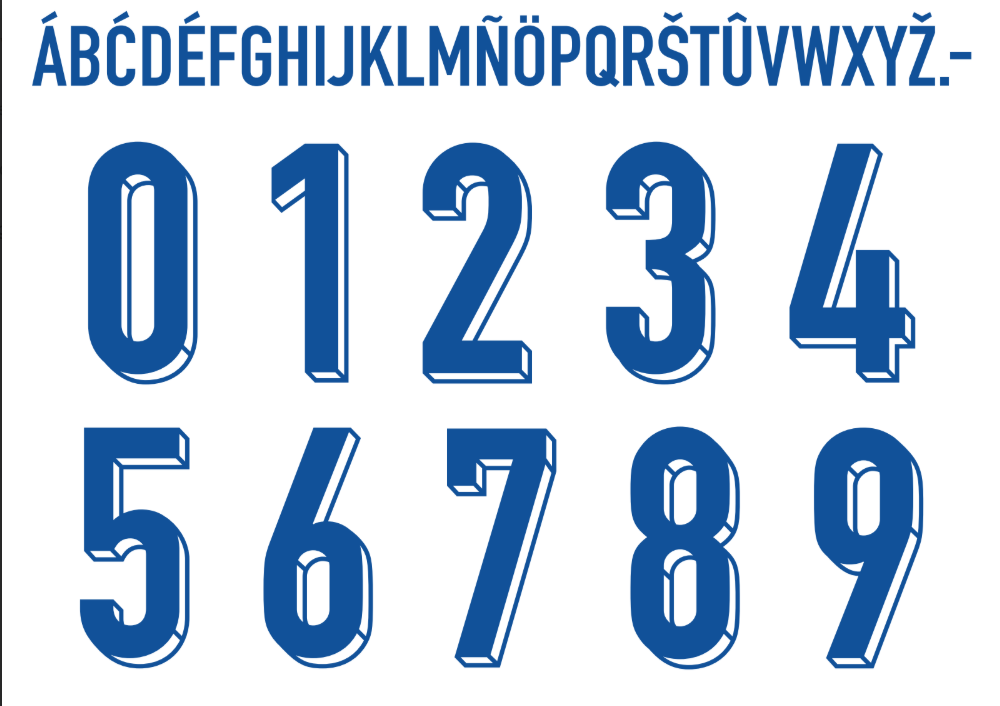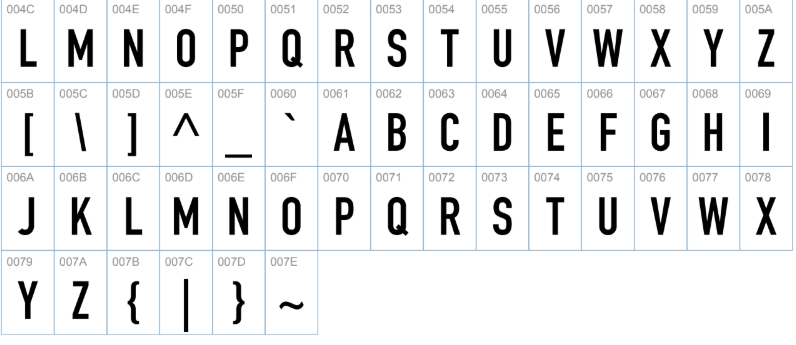
O futebol chinês continua buscando modernização e estilo visual, e o Shanghai Shenhua se destaca como um dos clubes mais tradicionais e populares da Chinese Super League (CSL). Para a temporada 2025/26, a parceria com a Nike, fornecedora exclusiva da liga, trouxe uma identidade visual renovada para os uniformes dos “Blue Devils”.
A tipografia utilizada nas camisas é um elemento crucial dessa estética. Seguindo os padrões globais da Nike para suas principais ligas, a fonte apresenta um design limpo, tecnológico e de alto contraste, garantindo leitura perfeita tanto nas transmissões em 4K quanto nas arquibancadas do Estádio de Shanghai.
Se você é designer, editor de patches para jogos como eFootball e FIFA, ou cria conteúdo sobre futebol asiático, este arquivo é essencial. Abaixo, você encontra a análise completa e o link para baixar a fonte Shanghai Shenhua 2025 – 26, uma recriação fiel inspirada na tipografia utilizada pelos jogadores na temporada atual.
Estilo visual da tipografia
A fonte do Shanghai Shenhua para 2025/26 reflete a filosofia de design da Nike para a Superliga Chinesa: funcionalidade aliada à modernidade.
- Geometria e Traços: A tipografia é sans-serif (sem serifa), com espessura média a grossa (Bold). Os números possuem um design geométrico com cortes angulares sutis, característicos das fontes esportivas contemporâneas, transmitindo velocidade e dinamismo.
- Aplicação no Uniforme: No uniforme titular (Home Kit), predominantemente azul, a fonte é aplicada geralmente na cor branca, garantindo contraste máximo. Já nos uniformes de visitante, as cores podem variar para se adaptar ao design da peça.
- Personalidade: O estilo é sóbrio e profissional. Diferente de ligas que apostam em fontes muito ornamentadas, a CSL e a Nike optaram por uma legibilidade universal, o que facilita a identificação dos atletas em qualquer mídia.